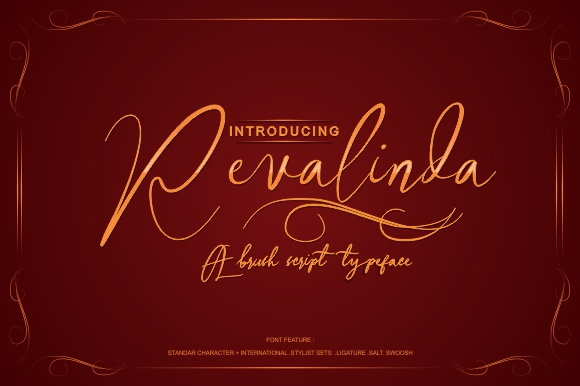
Revalinda Brush Stylist font – Download Grátis
Olá designers! Estou aqui uma fonte nova do nosso cantinho criativo, com a Revalinda Brush Stylist. Esta font é o resultado de uma fusão única entre o mundo da escrita a mão e os traços naturais das fontes digitais. Ela oferece um olhar delicado e encantador, perfeitamente adaptável para trabalhos que desejam explorar um tema feminino. A Revalinda Brush Stylist se destaca por seu ar poético e versátil, permitindo que você inove suas criações de design. Seja criando uma identidade visual feminina ou adicionando um toque delicado a um design gráfico tradicional, ela é ideal para isso. Se precisar de qualquer informação adicional sobre essa fonte especializada, fique à vontade para entrar em contato conosco. A designer, tepikalistudio, criou uma verdadeira joia gráfica que vai revolucionar como você trabalha com a escrita e o design. Esta é mais do que apenas um recurso de fontes; ela é uma colaboradora ativa no seu trabalho diário, fornecendo um toque único e personalizado para sua obra. Seja você designer de moda, publicitário ou criativo em geral, esta font pode ser a solução perfeita para dar ao seu design aquele toque especial. Por favor, faça deste o seu ativo favorito, ele é tão versátil quanto a natureza e tão delicado quanto uma folha d’água. Não deixe de conhecer mais sobre essa maravilha gráfica aqui na tepikalistudio. Comece com uma fonte que se assemelha ao toque natural da escrita, pois é sempre o primeiro passo para criar algo realmente único e atraente.